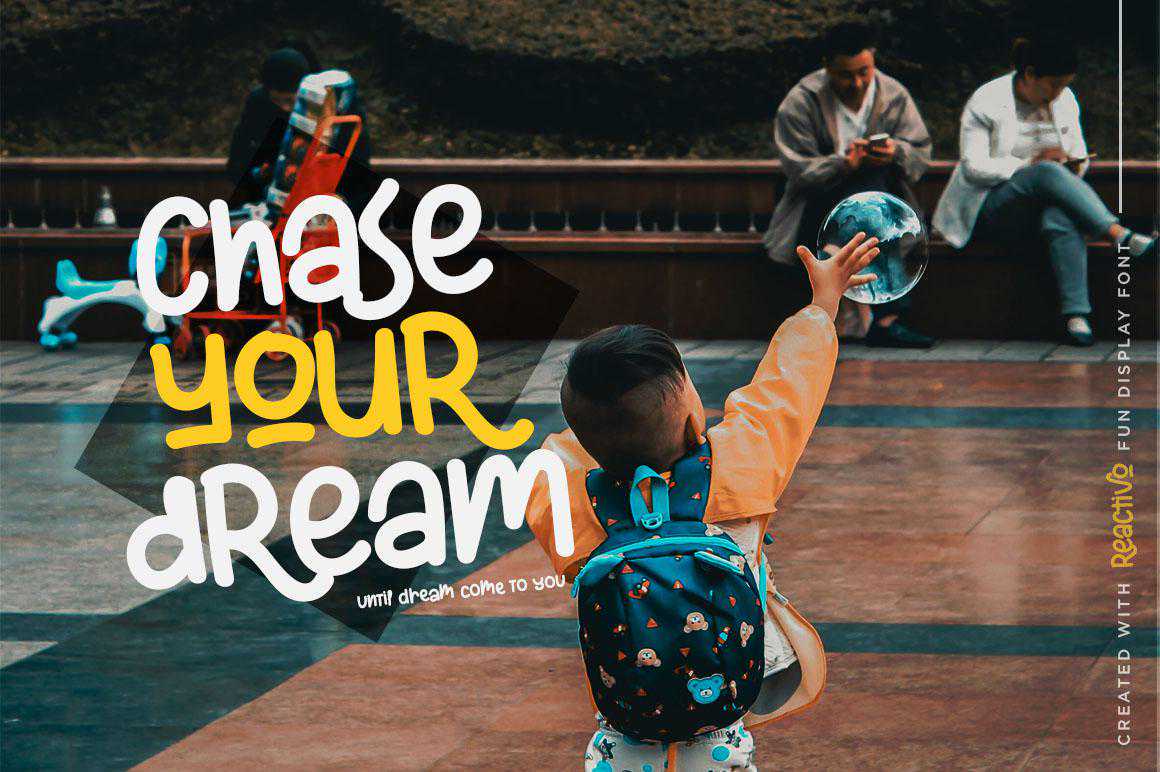
Reactivois Fund DisplayFont,使您的项目如Web设计横幅和PosterLooks更快乐,并且使您的项目更适合于需要帮助的项目。我通常认为,Reactivois Fund DisplayFont,使您的项目如Web设计横幅和PosterLooks更快乐,并且使您的项目如Web设计横幅和PosterLooks更快乐,非常适合所有需要朋友支持的项目。通常,您可以选择需要朋友支持的项目、横幅和网站设计。